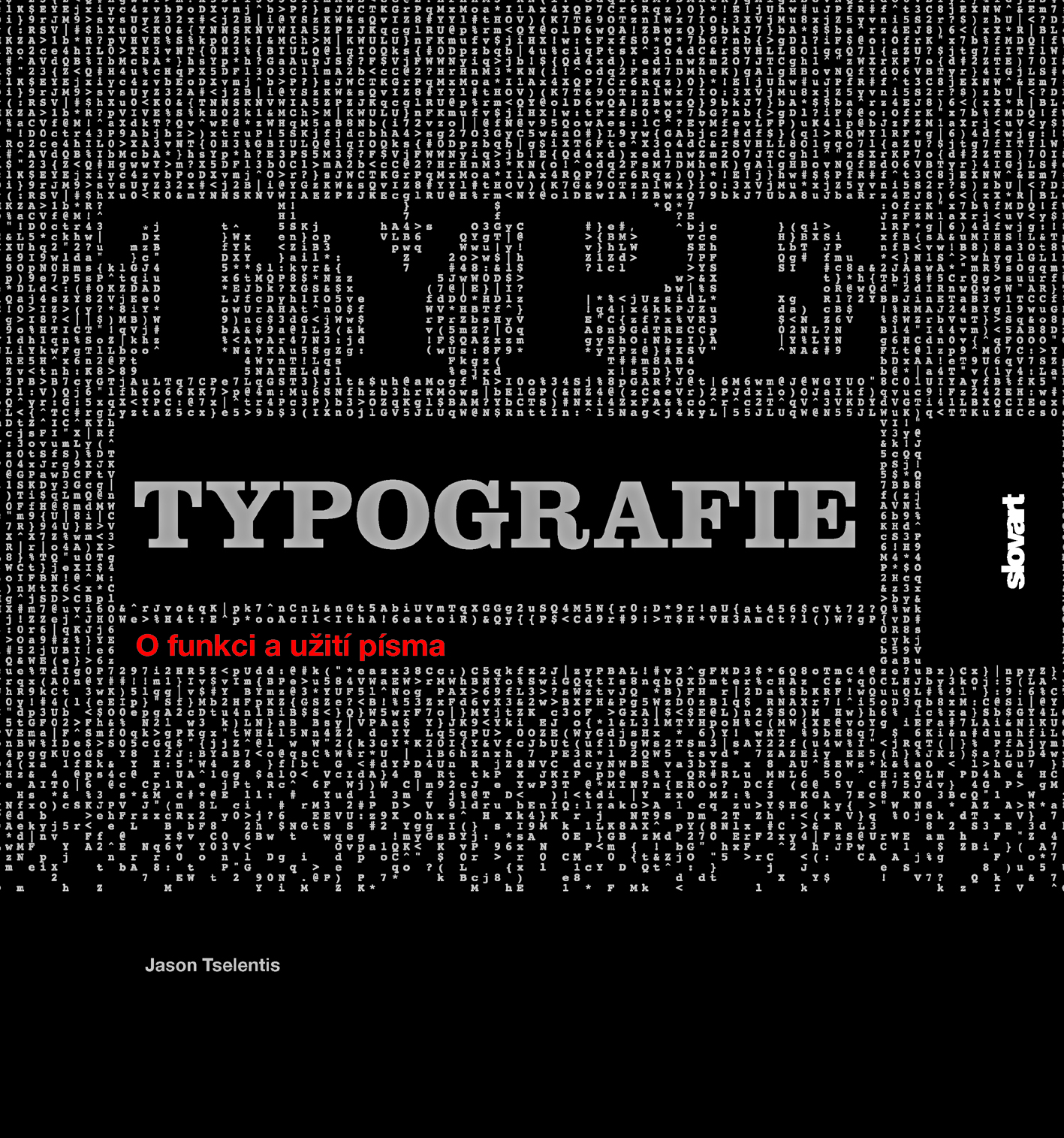
Typografie písma
Kniha je užitečným a vyčerpávajícím typografickým průvodcem, který nesmí chybět v knihovně žádného milovníka grafického designu. Zabývá se vlivem moderní typografie, vrací se zpět v čase a zkoumá milníky vývoje logotypu, layoutu, zaměřuje se na vliv písma, přičemž zdůrazňuje typografické základy grafické práce.